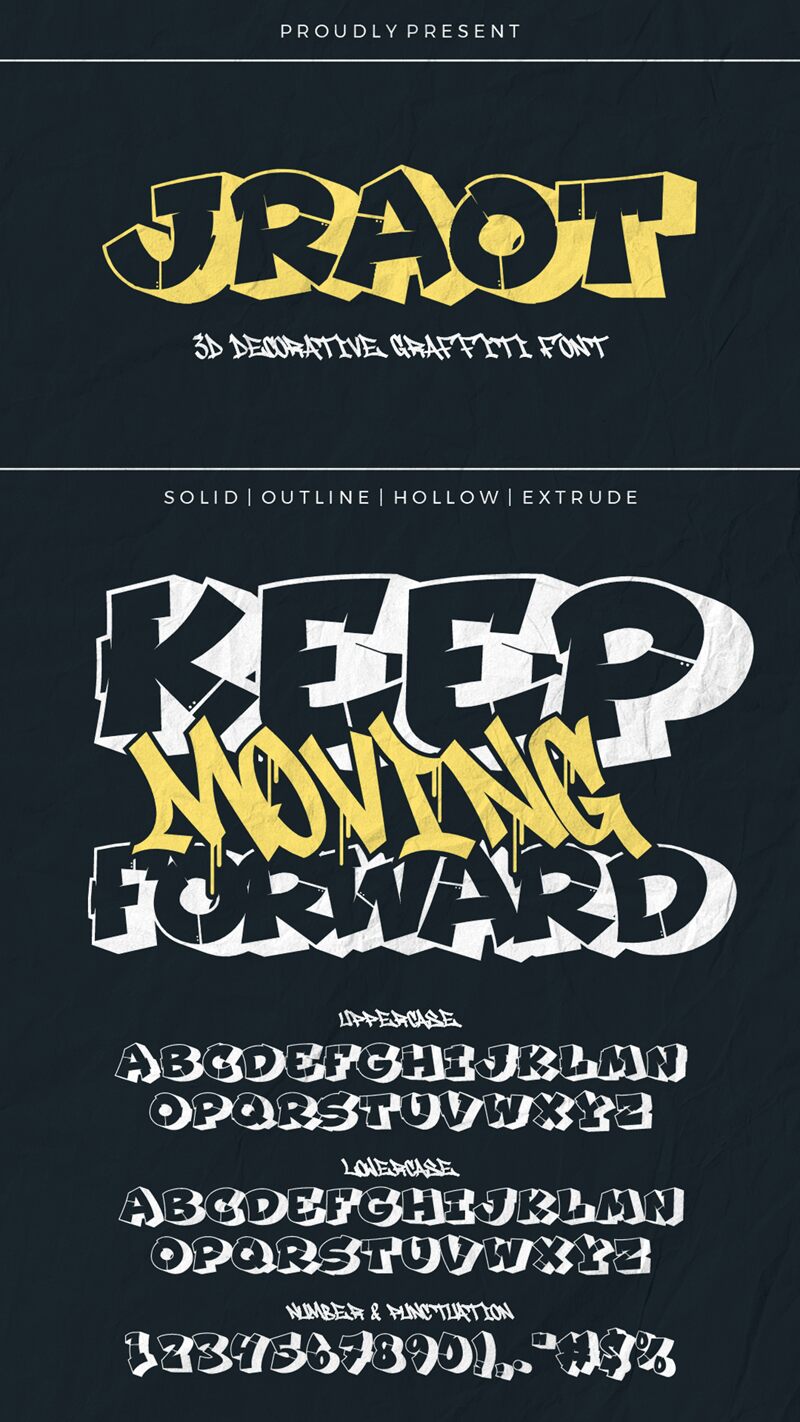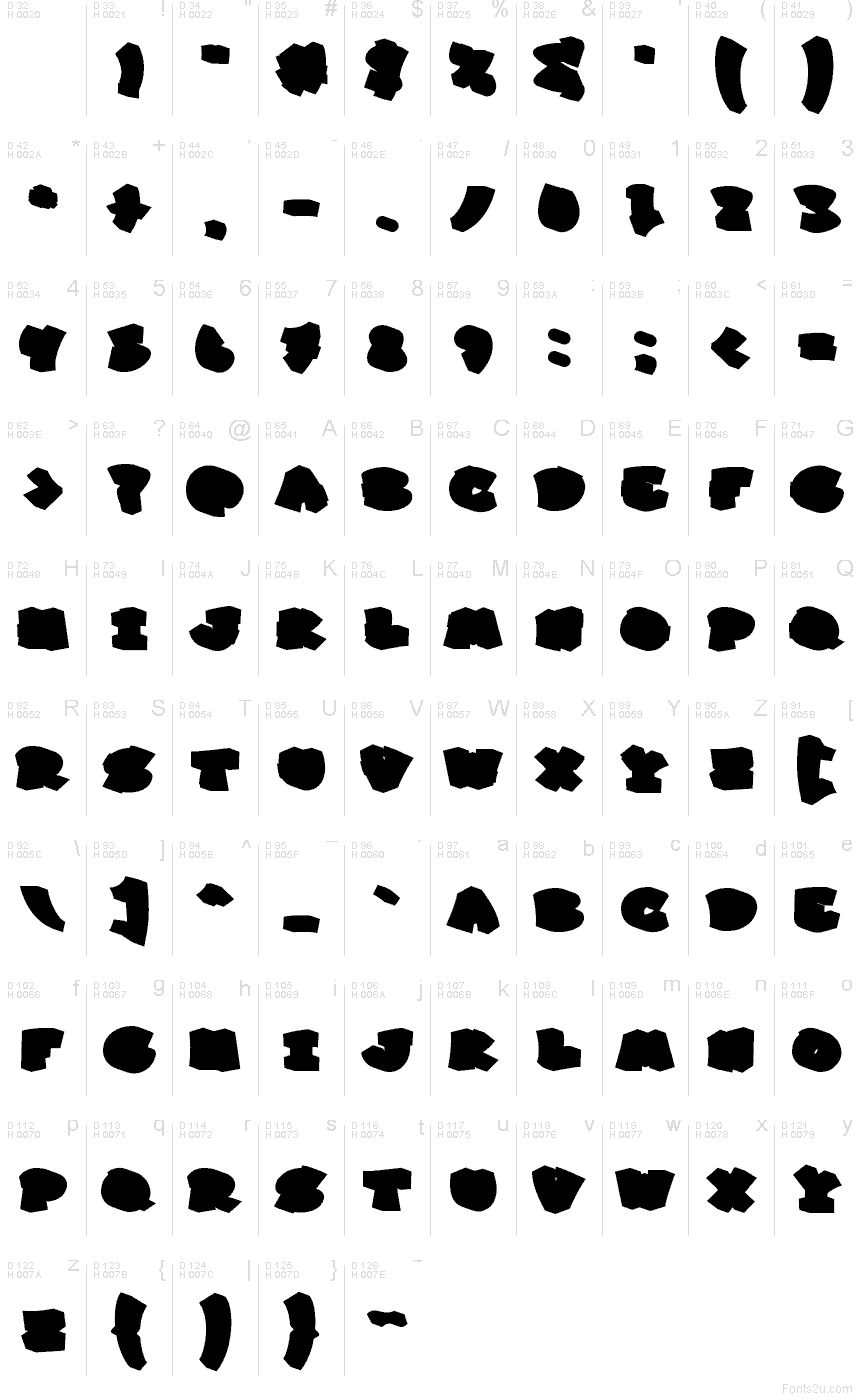
Jraot Extrude, bezplatné graffiti písmo od Sipanji x Cikareotype, sází na nafouknutou, podsaditou siluetu, která působí, jako by byla vytlačena ven ze středu. Široké tvary, useknuté rohy a zaoblené kontury vytvářejí vizuální dojem malovaného „throw-upu“ namísto uhlazeného grafického designu.
Tento tvar dodává krátkým textům silný charakter, což se skvěle hodí pro streetwearovou grafiku, hudební letáky, herní bannery, titulky plakátů nebo branding ve stylu nálepek. Protože jsou znaky kompaktní a výrazné, aniž by spoléhaly na složité detaily, Jraot Extrude skvěle funguje všude tam, kde chcete graffiti energii bez nutnosti přidávat kapající barvu, praskliny nebo jiné efekty.